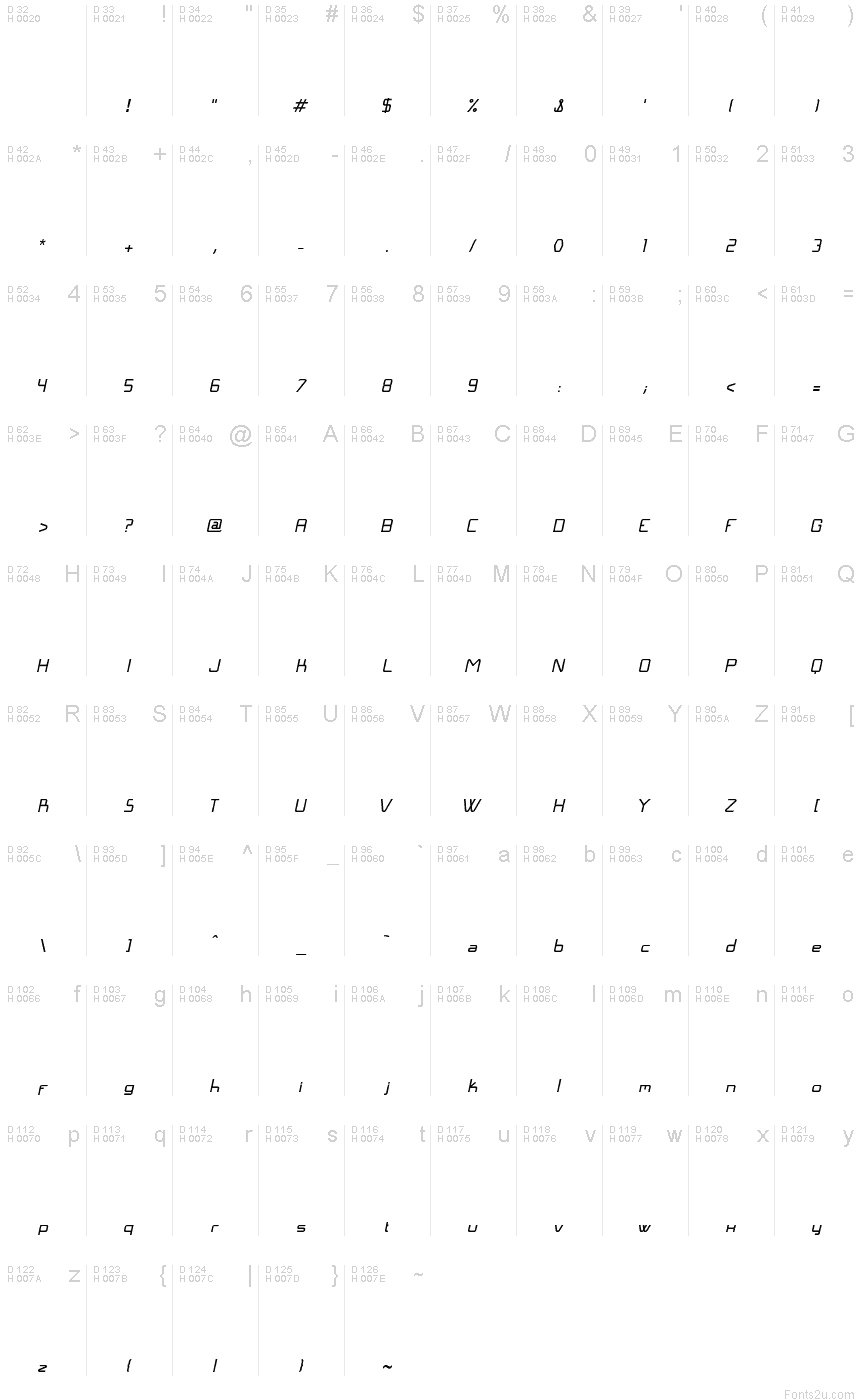
Langó Italic
Langó Italic di Bellart e Astramat Antaviana Type Division è un font display moderno caratterizzato da una marcata inclinazione, angoli arrotondati e tratti fluidi e snelli. Le minuscole mantengono un ritmo tecnico e compatto, dall’aspetto grafico ma mai rigido.
Langó Italic è perfetta per logotipi, titoli di poster, copertine musicali, packaging e brevi accenti editoriali, dove la spinta laterale conferisce dinamismo al nome. Si adatta inoltre alla segnaletica e al design di copertine quando si desidera che una singola riga sostenga il layout senza troppi fronzoli.